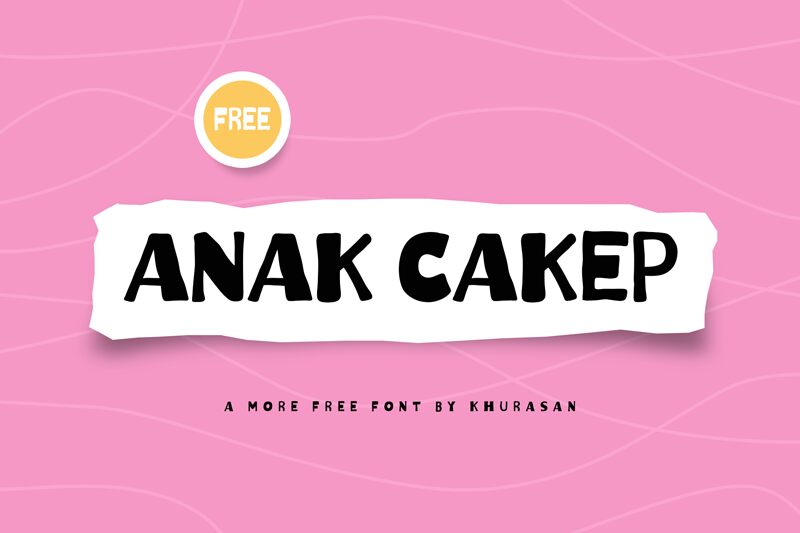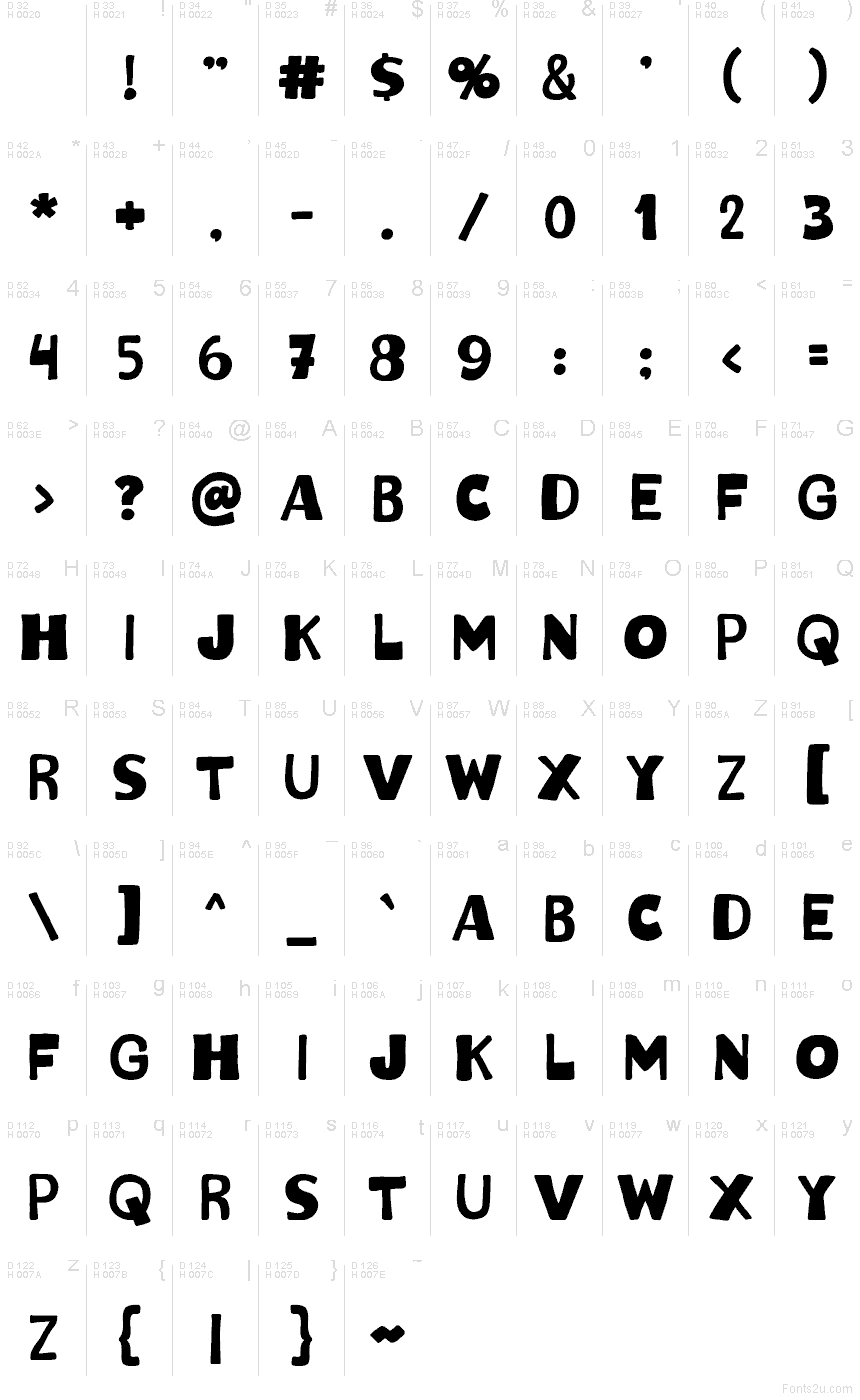
Anak Cakep par Khurasan est une police de caractères fantaisie gratuite de style cartoon, dotée de capitales épaisses et taillées à la main. L'épaisseur irrégulière de ses traits et ses coins doucement émoussés confèrent aux lettres une silhouette vivante et artisanale. Les formes penchent et gonflent dans différentes directions.
Les thèmes ludiques liés à l'alimentation s'y prêtent particulièrement bien, ce qui la rend utile pour l'emballage de snacks, l'identité visuelle de boulangeries et les affiches de fêtes d'enfants. Ses formes irrégulières peuvent rappeler des gâteaux, des étiquettes ou des mascottes dessinés à la main, mais la police s'avère particulièrement convaincante lorsqu'un projet nécessite un style de lettrage joyeux et volontairement imparfait.